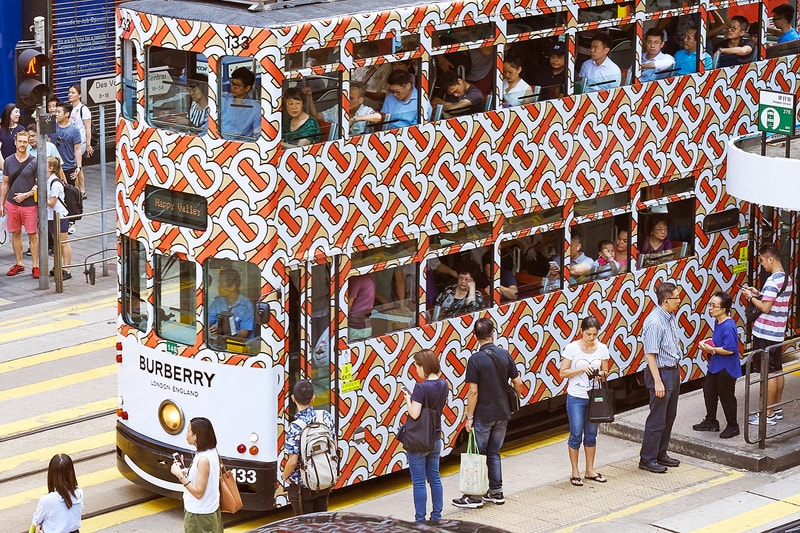
전 세계를 도배하고 있는 새 버버리 모노그램 & 피터 사빌 로고
내 이름은 ‘토마스 버버리’.
업데이트: 버버리의 새로운 모노그램이 현재 게릴라 형식으로 각국의 도시를 도배하고 있다. 런던, 뉴욕뿐만 아니라 서울, 홍콩, 상해까지 길거리 곳곳은 물론이고 건물과 버스, 대형 풍선 인형까지 장식했다. 아래 성수동과 이태원에 자리한 버버리 벽과 다른 장소의 모노그램들을 살펴보자. 이번 달 런던 패션위크에서 최초로 공개되는 리카르도 티시의 버버리 컬렉션도 기대하시길.
8월 3일 기준: 크리스토퍼 베일리를 대신해 리카르도 티시를 크리에이티브 본부 사령탑에 앉힌 버버리. 티시 영입부터 줄곧 비비안 웨스트우드와 협업할 것이라는 소문과 함께 브랜드가 새바람을 위한 대대적인 변화 전략을 모색하고 있다는 풍문이 들려왔다.
변화는 모노그램부터 시작되었다. 패션 하우스 설립자의 이름을 딴 새로운 모노그램  ‘토마스 버버리’를 선보인 것. 그간 디올과 펜디 등 많은 브랜드가 자신들의 아카이브에 파고들며 초기의 복고풍 프린트를 부활시켰지만, 버버리는 시그너처 하우스 체크를 고수했다는 점에서 상징적이다. ’토마스 버버리’는 리카르도 티시와 그래픽 디자이너 피터 사빌간에 오간 버버리 2019 봄, 여름 컬렉션 쇼 초대 이메일을 통해 공개되었다. 황금색 배경에 오렌지색 격자 무늬가 가득하고 그 위에 하얀색 ‘B’ 문구가 반복되는 디자인이다.
버버리는 신규 모노그램과 함께 사빌이 디자인한 새 로고도 공개했다. 역시 피터 사빌의 작품. 더욱 대담하고 현대적인 변화를 꾀하려는 움직임을 상징하는 버버리의 새 모노그램과 로고를 아래에서 감상해보자.